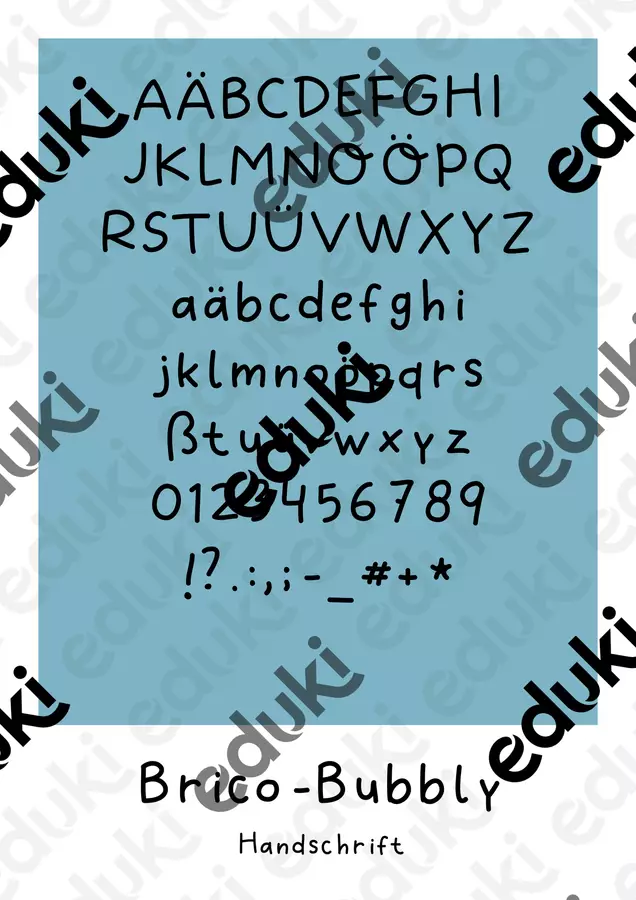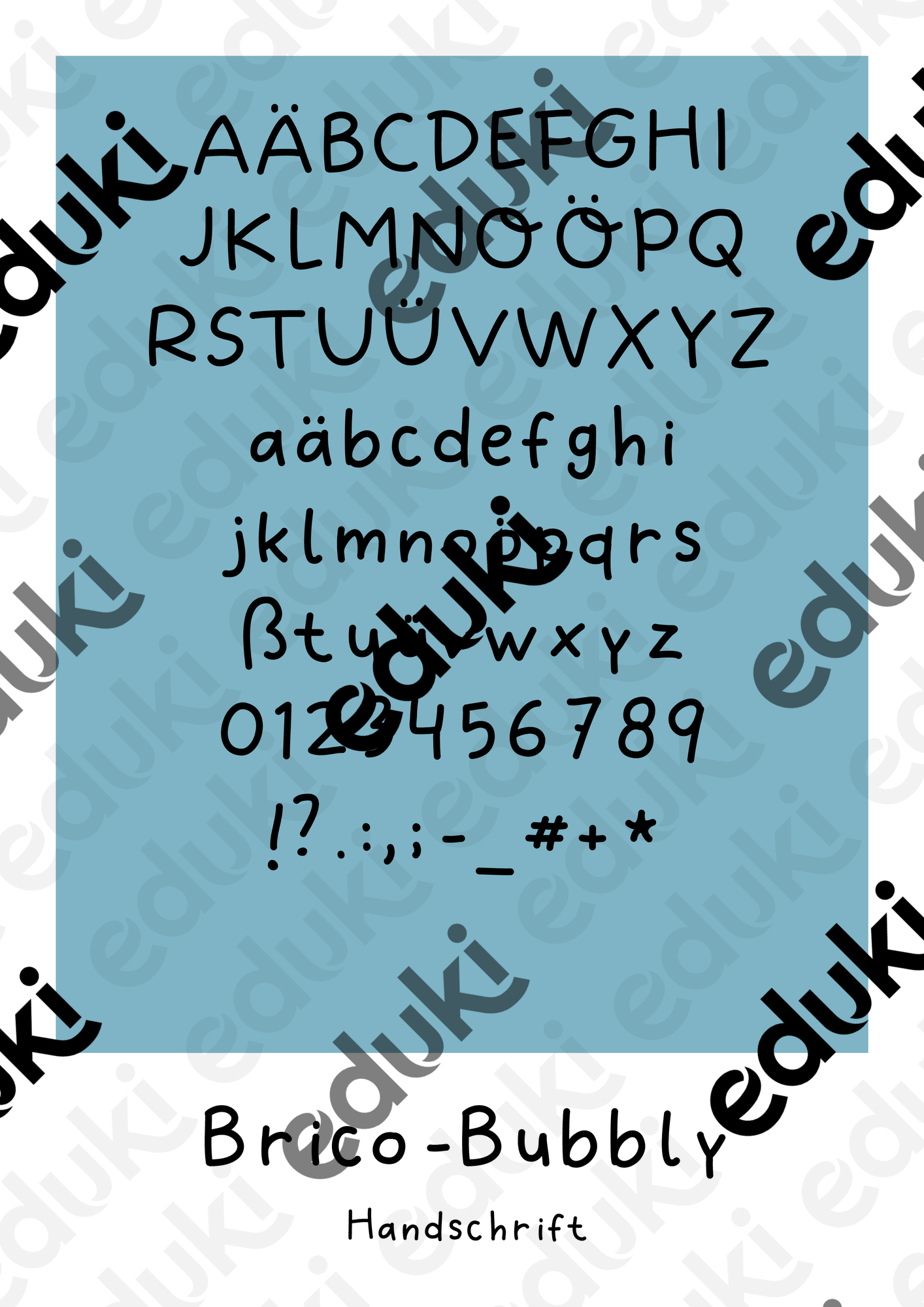
Selbsterstellte Handschrift die sich wunderbar zur Erstellung von Arbeitsblättern oder anderem Unterrichtsmaterial eignet.
Schriftart für dein Arbeitsmaterial - BricoBubbly